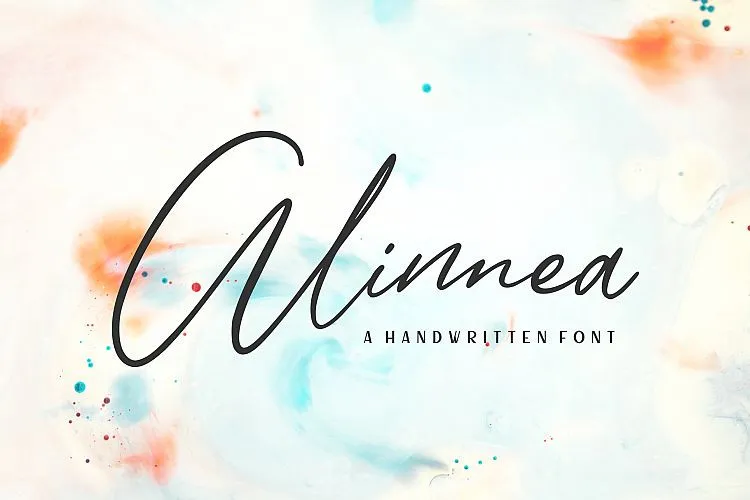
Alinnea Signature Font – Download Grátis
Olá amigos! Estou aqui uma sugestão para quem procura um novo recurso visual para seus projetos. Alinnea Signature Font é uma fonte de escrita à mão livre natural, criada pela Garisman Studio e compartilhada pelo designer 0001themes. Esta fonte é perfeita para os mais diversos tipos de projetos — desde logomarcas e convites até designs de casamento e redes sociais. Alinnea vem repleta de energia, permitindo que você crie e personalize seus trabalhos em um instante. É uma excelente opção para anúncios, embalagens de produtos, design de produto, rótulos, fotografia ou mesmo para adicionar aquele toque especial a eventos especiais. Alinnea Signature Font é ideal tanto para os que buscam uma sensação moderna e elegante quanto para quem quer algo mais quente e pessoal, com um toque autêntico de escrita à mão. Se você está procurando por uma fonte de escrita à mão livre natural, sem dúvida Alinnea Signature Font será a escolha perfeita. Com sua intensidade única e a modernidade refinada, ela se ajusta ao seu projeto com uma facilidade impressionante. Esse recurso gráfico é um verdadeiro acréscimo para qualquer trabalho que você esteja realizando, seja em redes sociais, embalagens de produtos ou até mesmo no design de casamento. Alinnea Signature Font é a fonte perfeita para quem procura algo mais que uma simples fonte padrão, mas sim algo que reflete sua personalidade e estilo único.